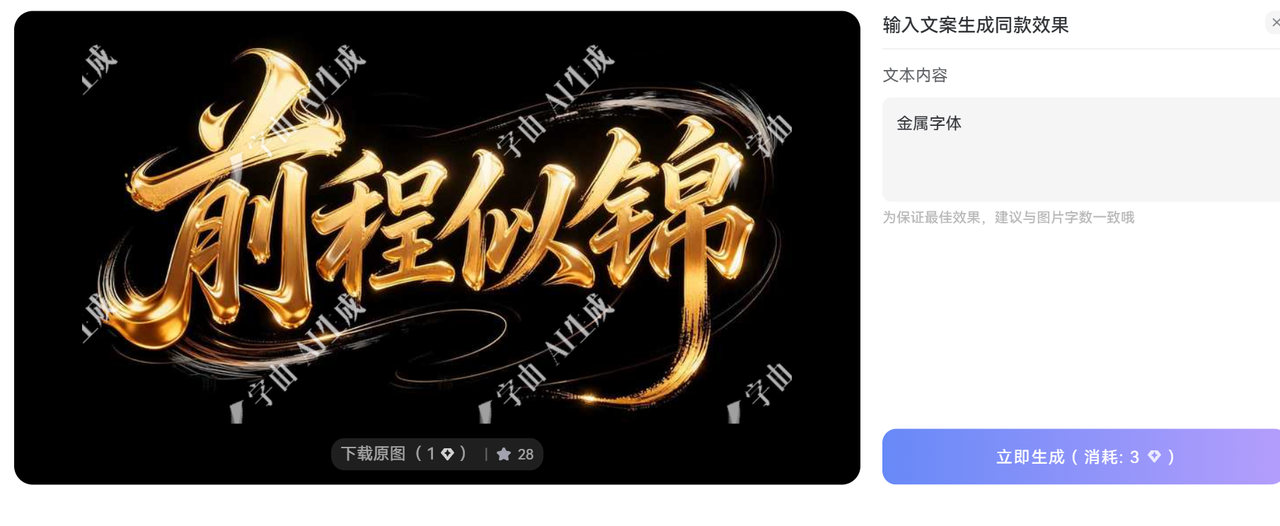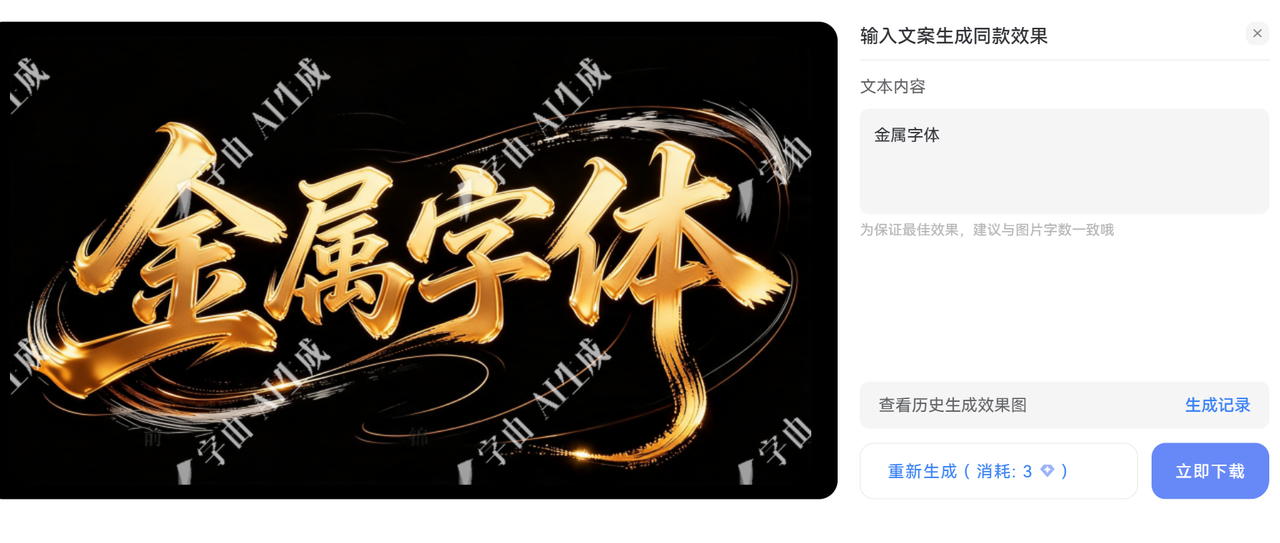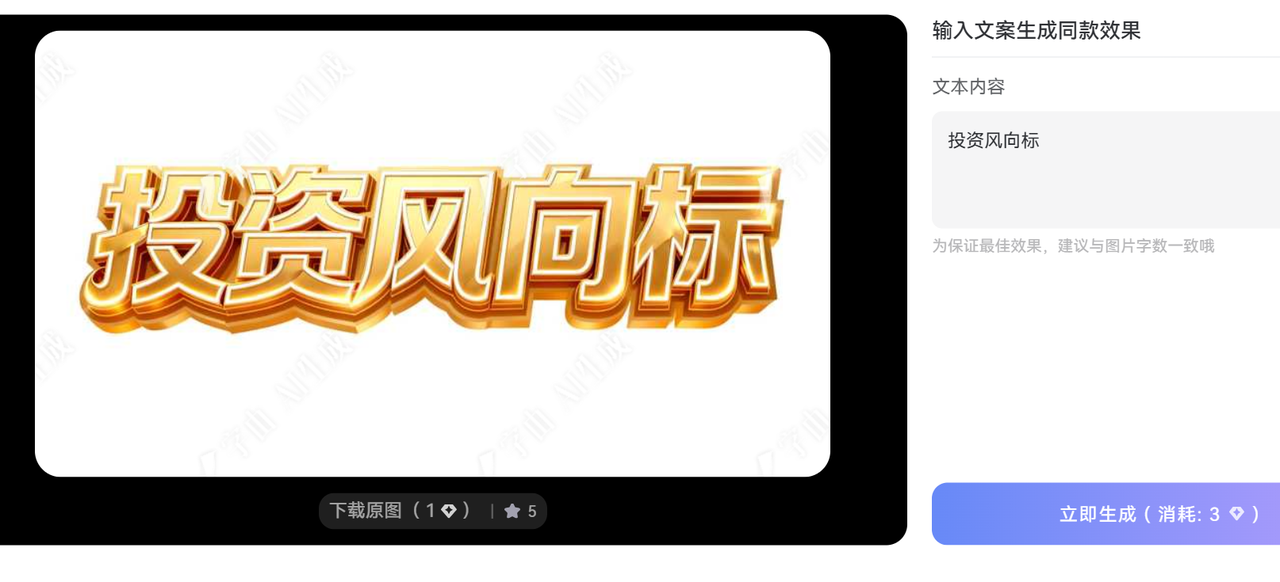
免费商用金属字体哪里找?试试AI生成金属字体
做设计这几年,我遇到最头疼的事就是找金属质感的字体。每次做海报、Logo或者产品包装,客户总说"要那种有金属感的,酷炫一点的"。我翻遍各大字体网站,发现效果根本不是我想要的。本文教你如何使用 AI 生成金属字体,帮你解决金属字体的查找和使用问题。
为什么金属字体这么难找
金属字体的特殊性在于它的制作成本高。设计师需要做出金属的光泽、纹理、立体感,这比普通字体复杂得多。所以市面上真正高质量的金属字体,大多数都要付费授权。免费的要么质量差,要么只能个人使用,商业用途根本不敢碰。
我试过用PS自己加效果,把普通字体做成金属质感。但说实话,那个效果和专业金属字体比起来差太远了。而且每次都要重新调参数,特别浪费时间。
使用字由AI字体生成金属字体
打开字由AI字体页面,筛选字体风格为“金属”,或者直接在搜索框中搜索“金属”,快速找到金属字体模板
选择一款你喜欢的字体模板,输入自己的文字,点击一键生成,就能生成同款金属字体。
看下面的生成图,体验下什么叫做一键生成同款,和模板中的字数相同,会在效果上表现更好。
立即生成金属字体下载使用字体,如果对生成效果比较满意,可以把金属字体下载到本地,应用到其它设计工具中。
推荐几款金属字体模板
投资风向标
非常适合金融行业的金属字体
金榜题名
非常适合高考、中考、考研等场景
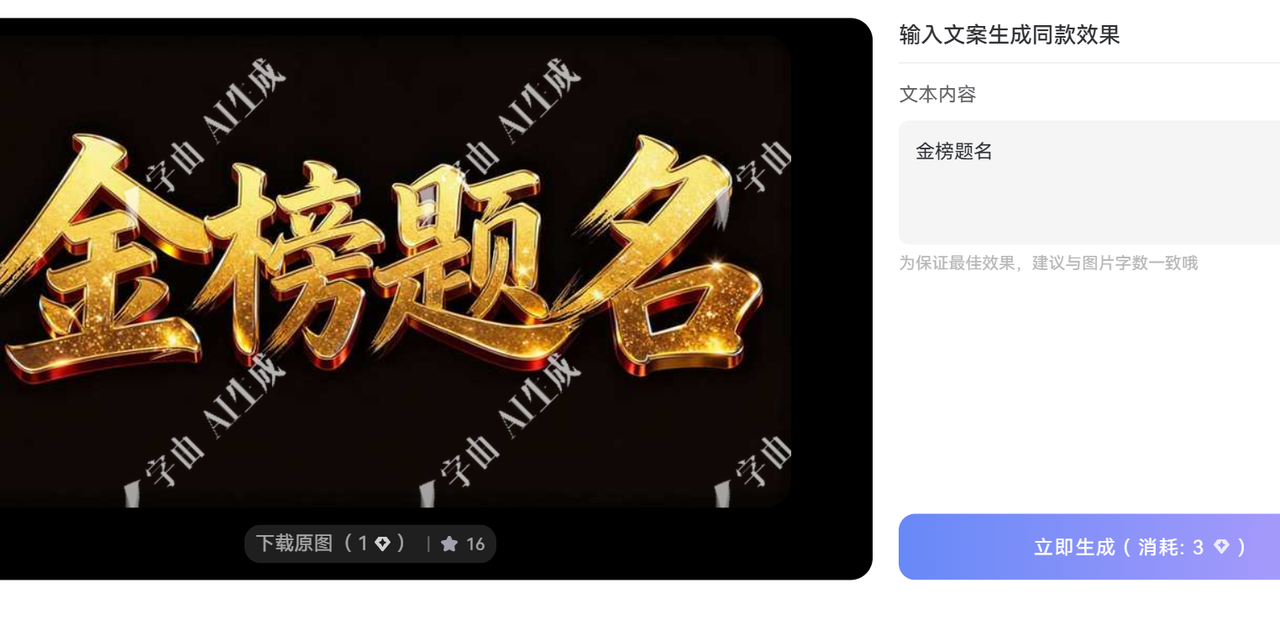
周年庆典
时候电商活动、公司活动等场景